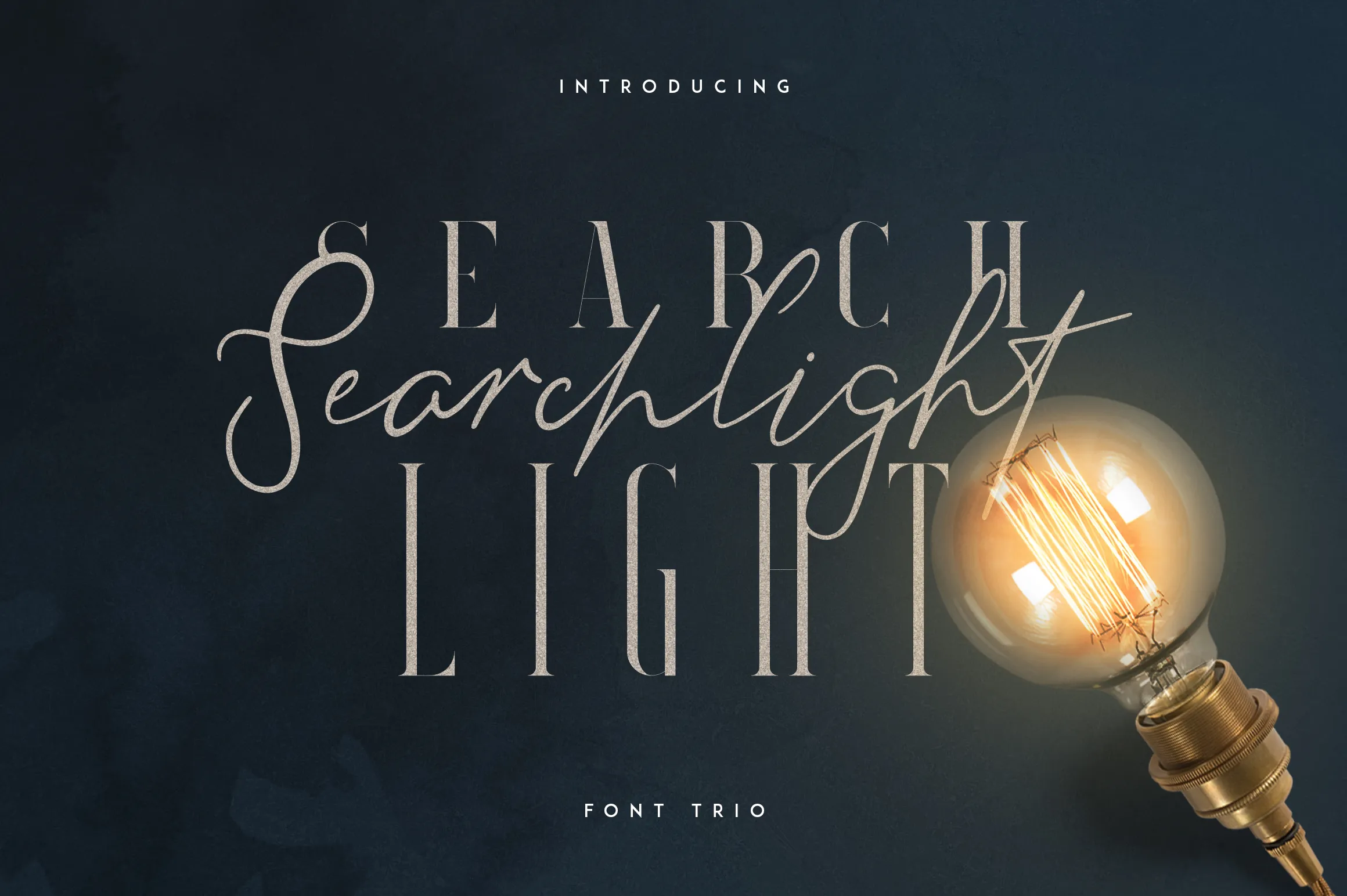
Searchlight Font Trio – Download Grátis
A Searchlight Font Trio é uma trindade elegante de fontes vintage criada para oferecer diversidade e versatilidade ao design. Esta família de fontes vem com três estilos únicos, juntamente com ligaturas meticulosamente projetadas para garantir um texto atraente em qualquer tamanho. Com suporte multilinguístico, a Searchlight está equipada para atender às necessidades dos designers que buscam uma opção sofisticada e versátil, ideal tanto para uso no grande formato quanto para aplicação em detalhes finos do texto. Para os amantes de bom design gráfico, a Searchlight Font Trio é um excelente recurso para explorar diversos estilos clássicos e modernos ao mesmo tempo.